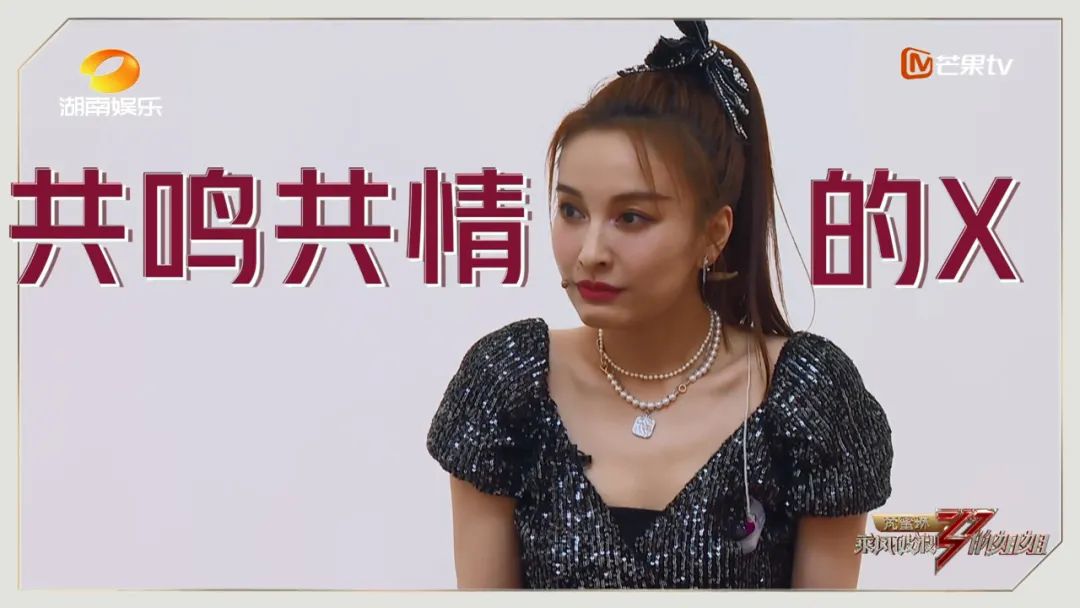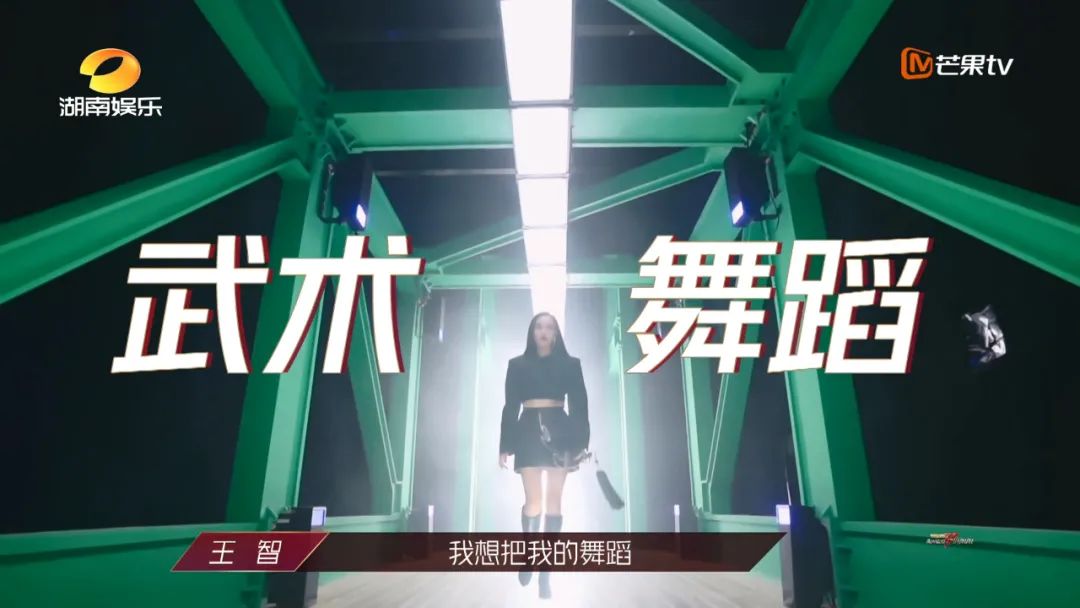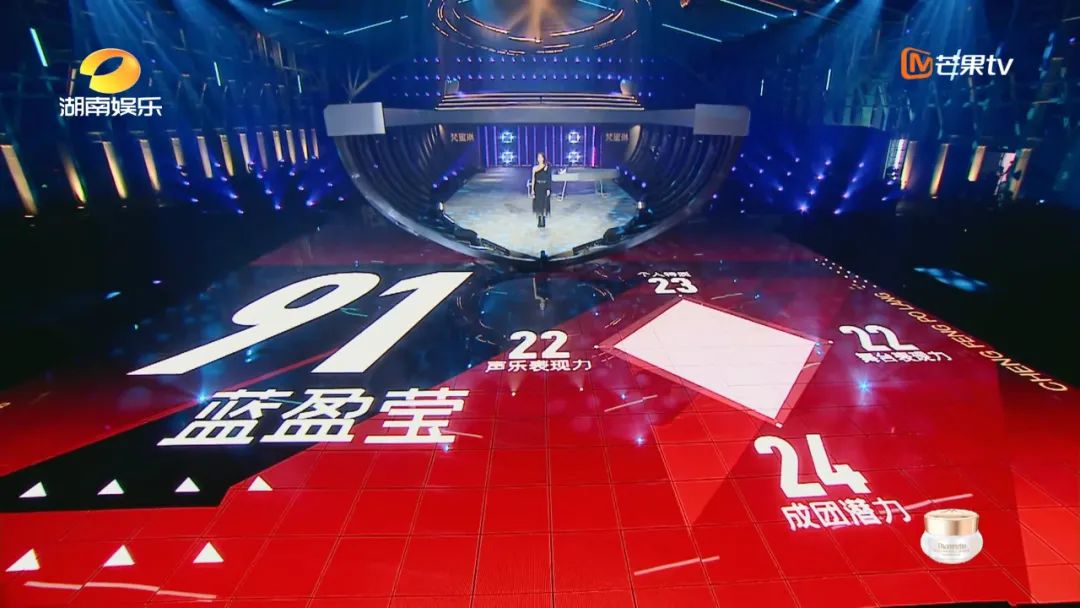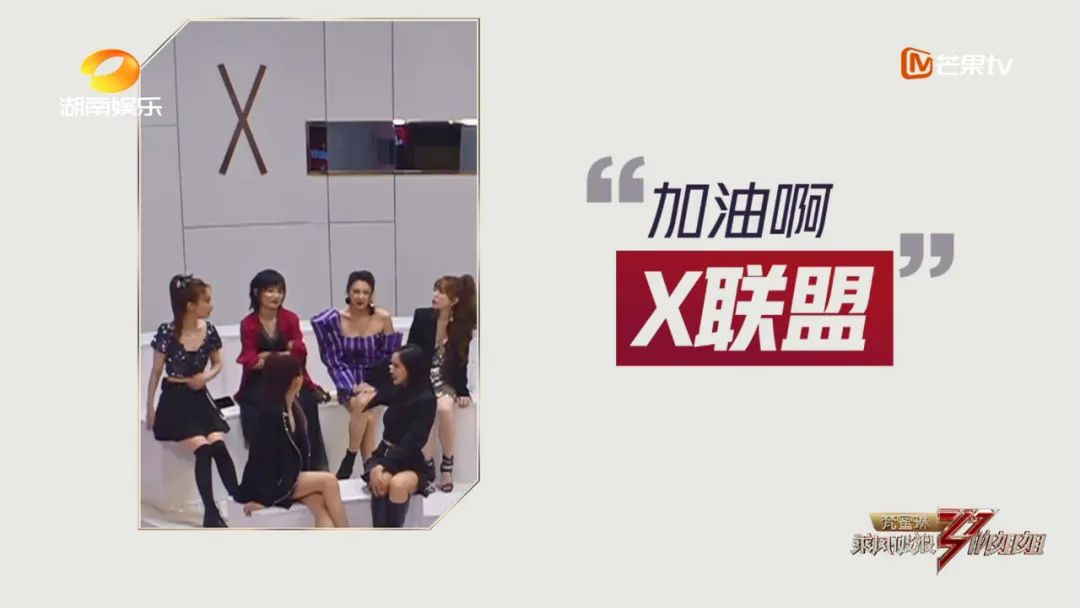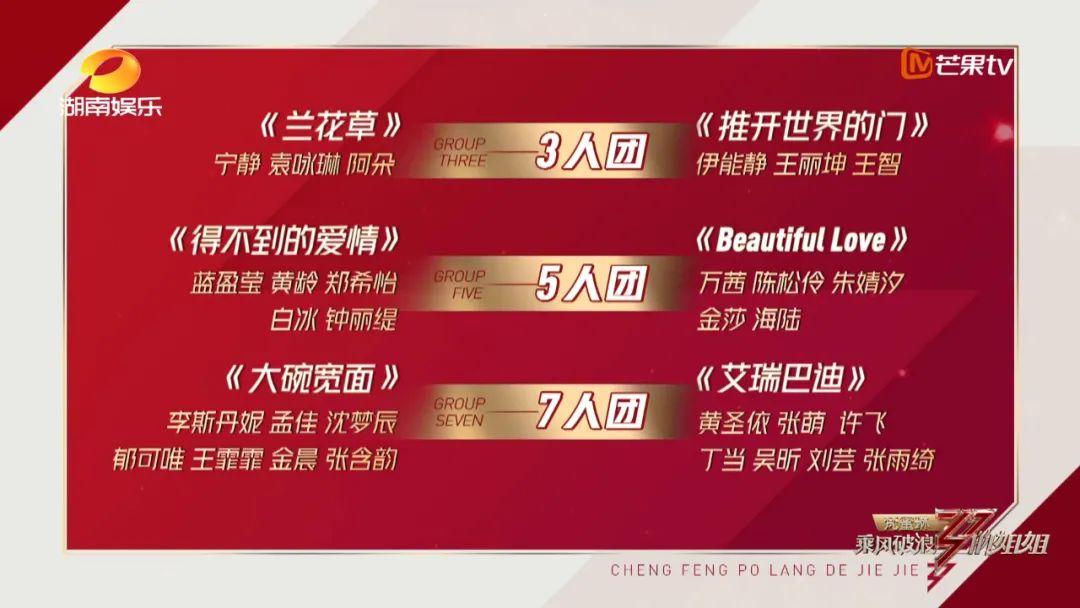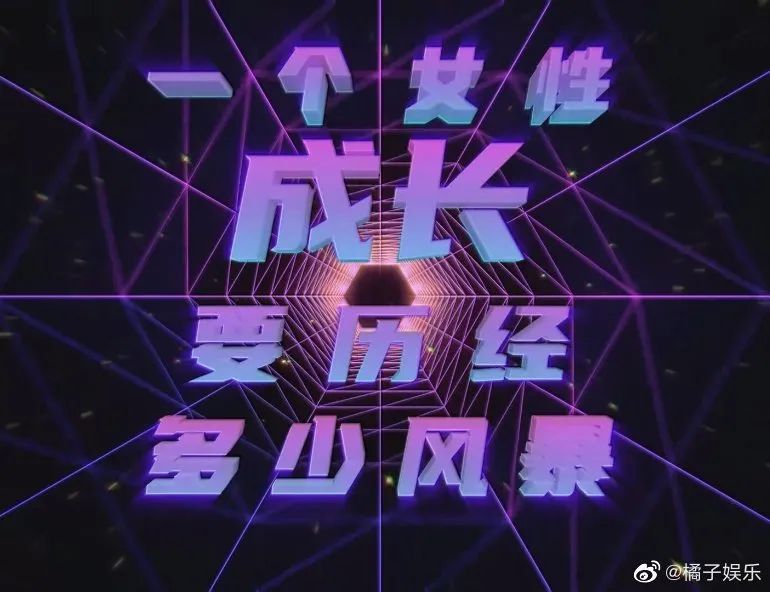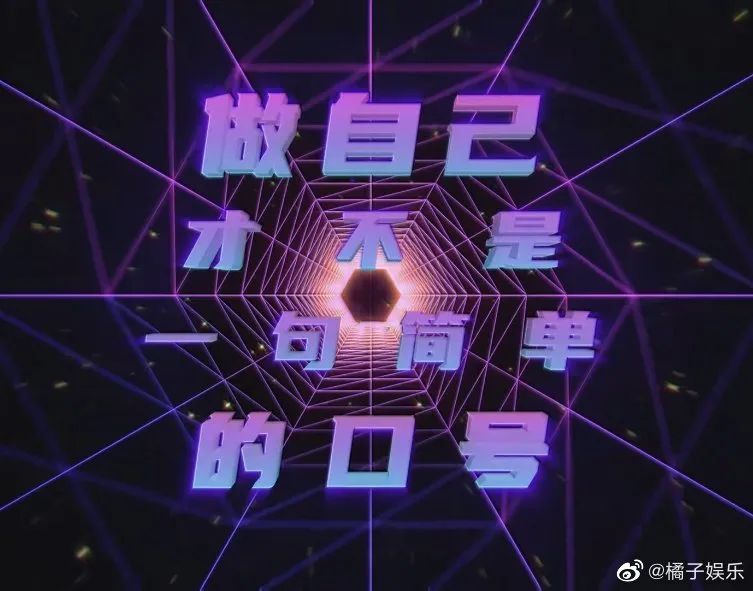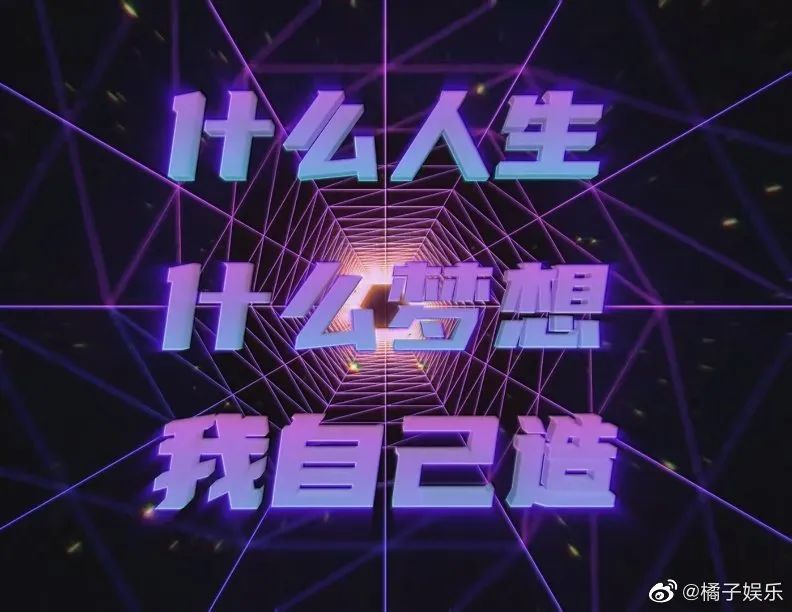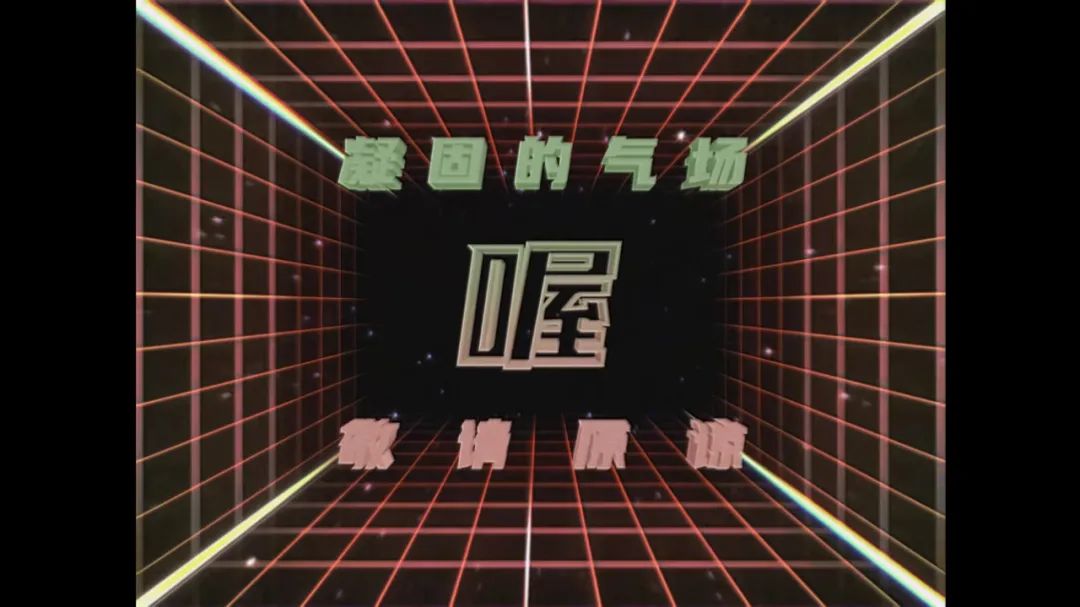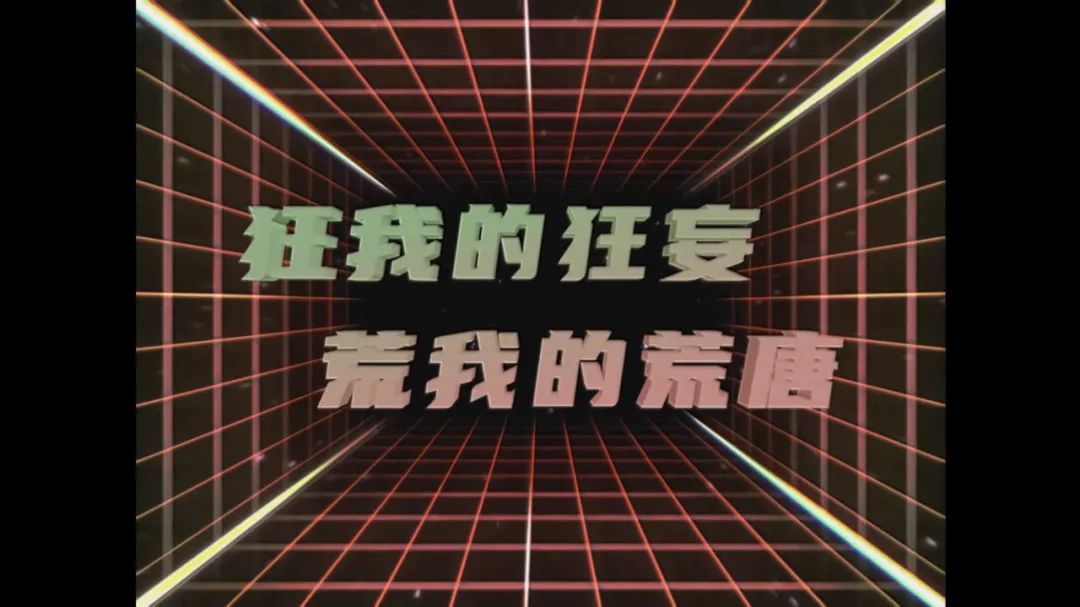
乘风破浪的姐姐,字体有点上头!
要说最近最火的综艺,非《乘风破的姐姐》莫属了吧,虽然开播得静悄悄,但前期撩得到位,所以话题度一直居高不下……
柚子也是一枚姐姐粉,第一期就追了好几遍,主要看商业互捧、帆船舞台、字体展现。
没错,都是30+的小姐姐,字体当然也要成熟、高级、有魅力,汉仪雅酷黑是个不错的选择!
除此之外,魔性洗脑的《无价之姐》,也用了字由X优设联合发布的优设标题黑。
整首MV几乎都是用重复原则,将字体按照一定规律、节奏连续排列,非常有视觉感染力~
所以你也会跟着音乐不停摇咿摇咿摇……
有人还以为这字体是特定的,因为非常契合。
但其实是优设标题黑自带倾斜的风格,让人上头~
你可以把它重复排版应用~
也可以把它扭曲旋转~
镂空拼接会有焕然一新的感觉~
放大铺满就是霸道总裁~